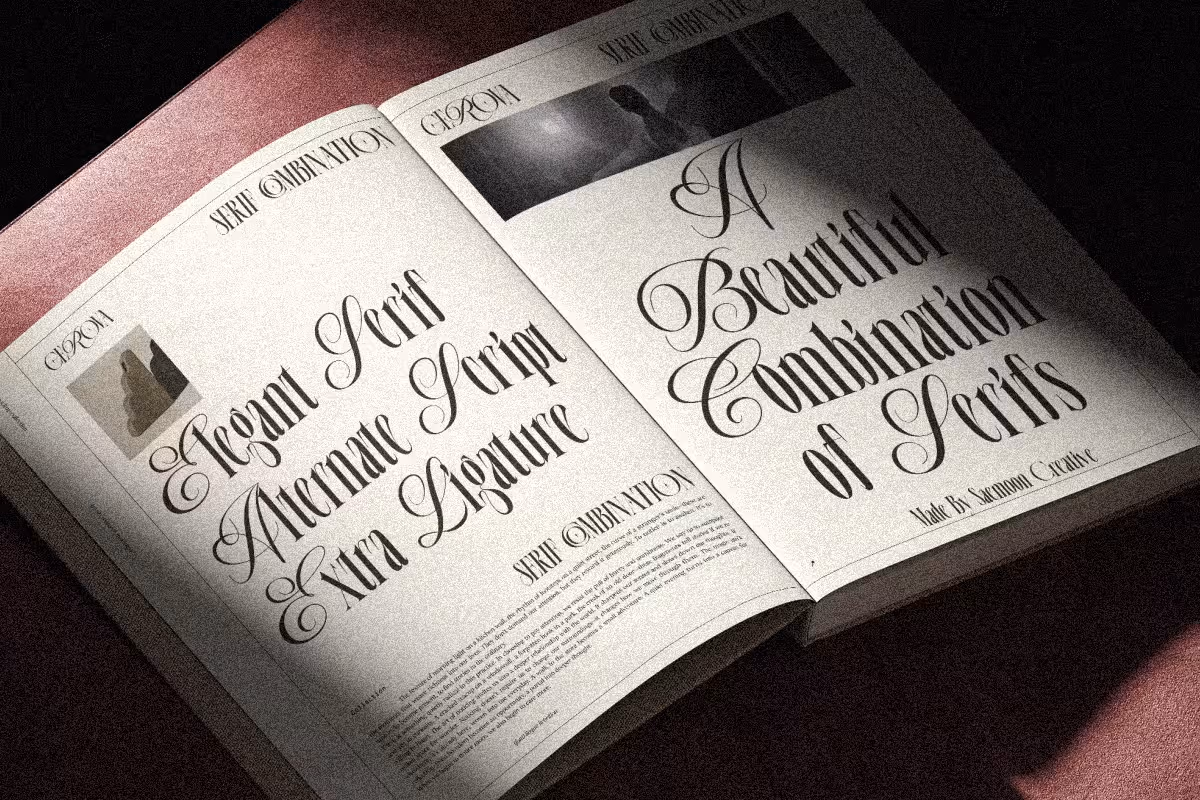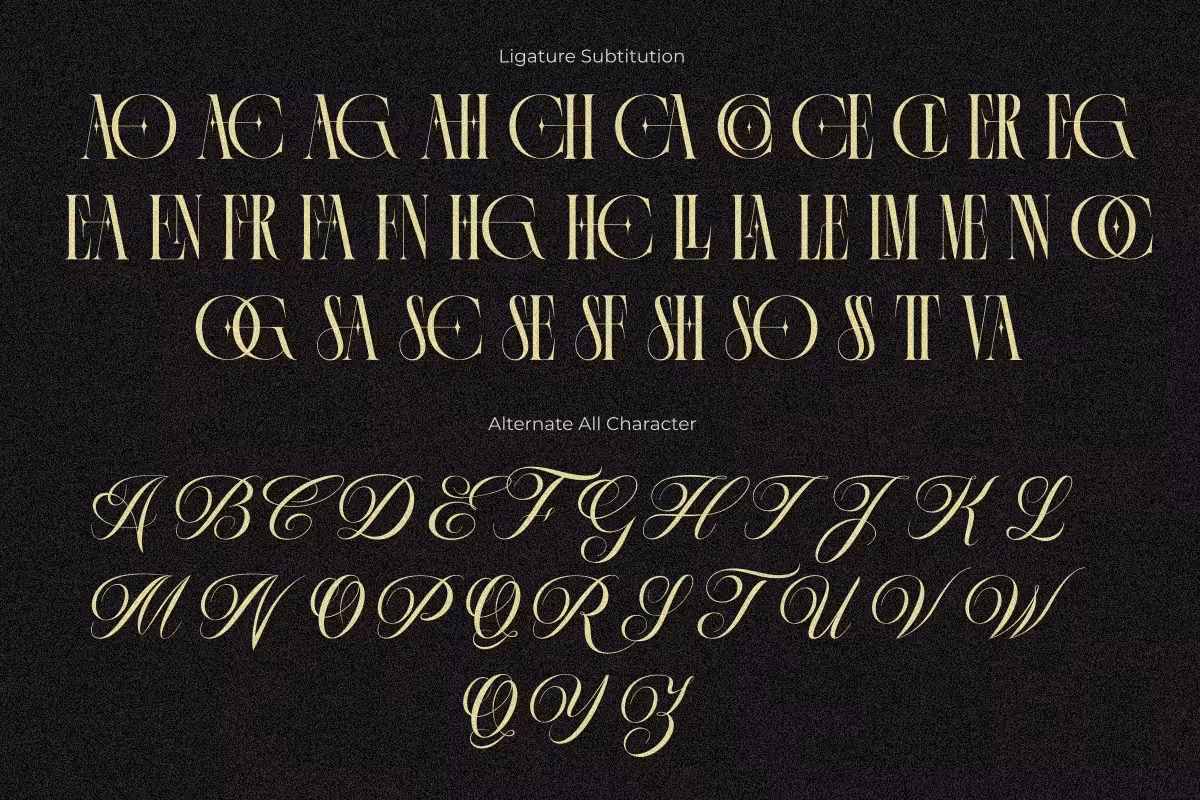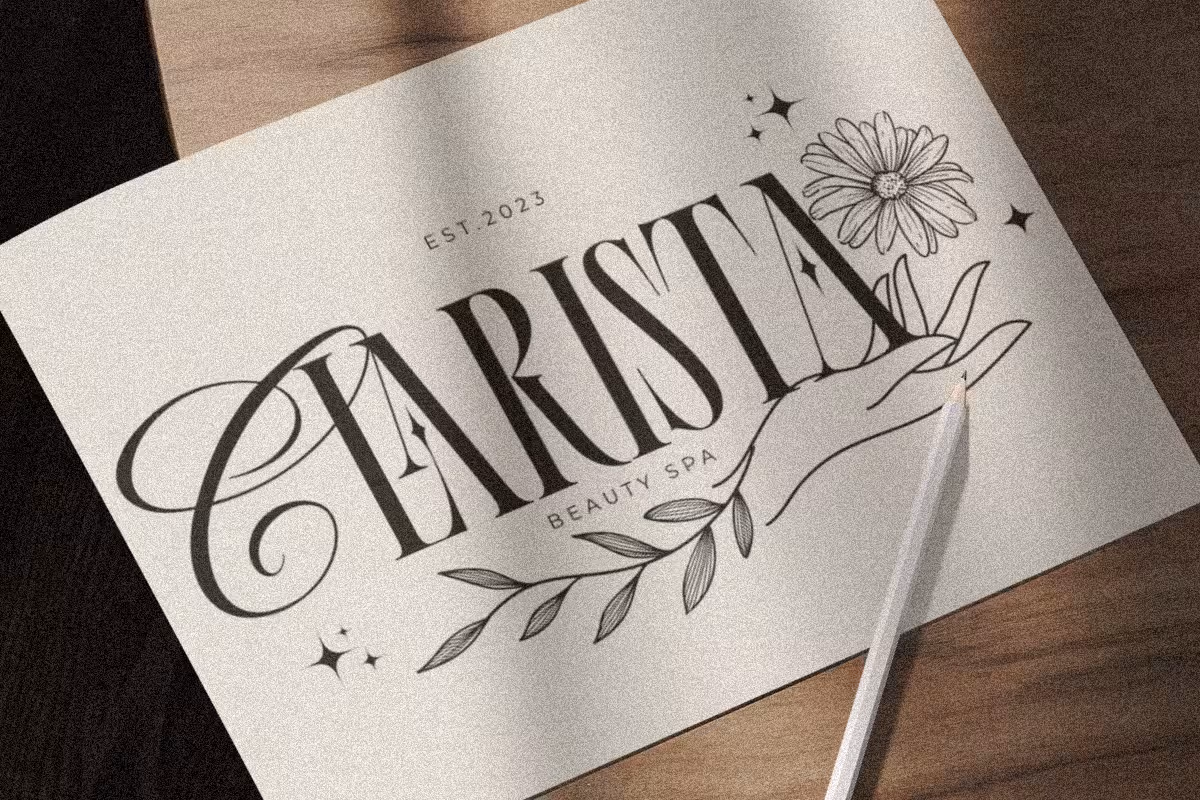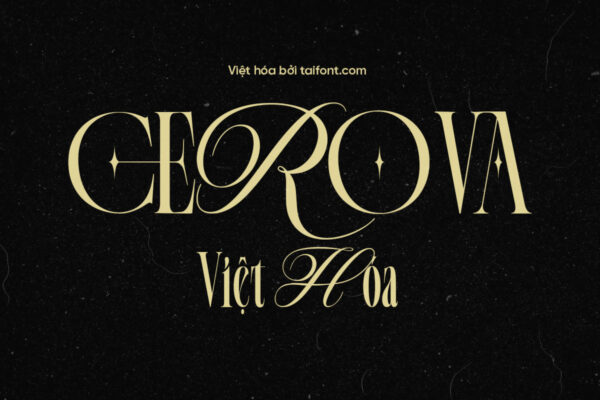
Giới thiệu về Font TF Cerova Việt hóa
TF Cerova Việt hóa là một font chữ có chân (serif) nổi bật với vẻ đẹp tinh tế và đẳng cấp, cùng với kho Glyphs (ký tự đặc biệt) phong phú. Được thiết kế tỉ mỉ, Cerova kết hợp hài hòa giữa nét cổ điển và sự hiện đại, mang đến sự sang trọng và khả năng tùy biến cao, giúp bạn tạo ra những thiết kế độc đáo.
Với sự linh hoạt và tính thẩm mỹ cao, TF Cerova là lựa chọn lý tưởng cho các ấn phẩm và thiết kế đòi hỏi sự tinh xảo:
- Thiết kế tạp chí: Hoàn hảo cho các tiêu đề bài viết, nội dung chính, hoặc các phần mục lục, giúp tạp chí trở nên cuốn hút, chuyên nghiệp và dễ đọc.
- Thời trang: Lý tưởng cho các thương hiệu thời trang cao cấp, nhãn mác sản phẩm, lookbook, hoặc các ấn phẩm quảng cáo, góp phần thể hiện sự tinh tế và đẳng cấp của bộ sưu tập.
- Ấn phẩm social đẹp: Tạo nên các thiết kế hình ảnh, bài đăng trên mạng xã hội với phong cách chuyên nghiệp, thu hút và khác biệt, phù hợp với các chiến dịch truyền thông cao cấp.
Với TF Cerova Việt hóa, bạn không chỉ có một font chữ đẹp mà còn là một công cụ sáng tạo mạnh mẽ, giúp bạn tạo ra những thiết kế thực sự ấn tượng, nâng tầm giá trị cho mọi dự án.
Font Việt hóa TF Cerova – Nhiều Glyphs, font cho MV ca nhạc